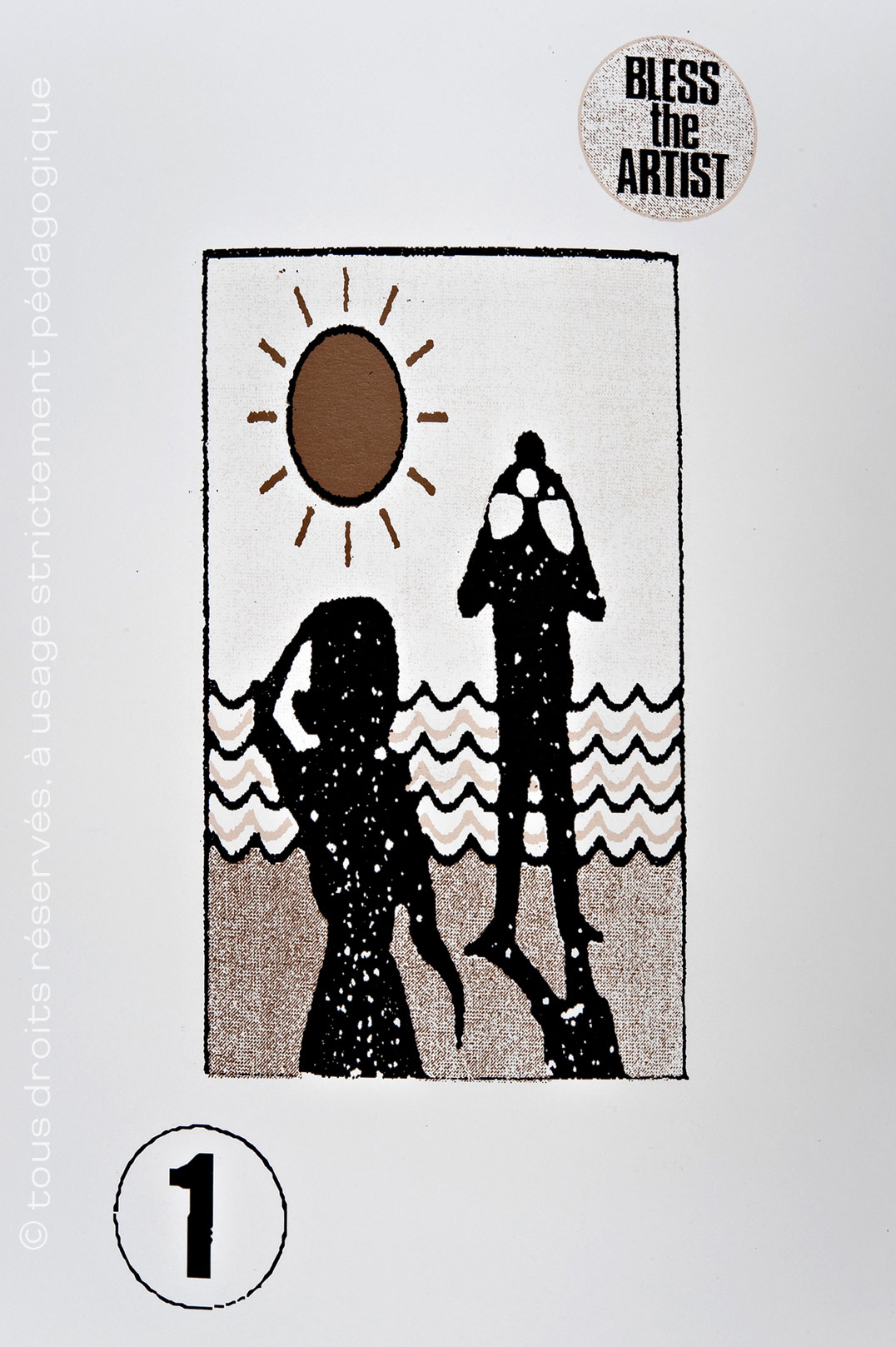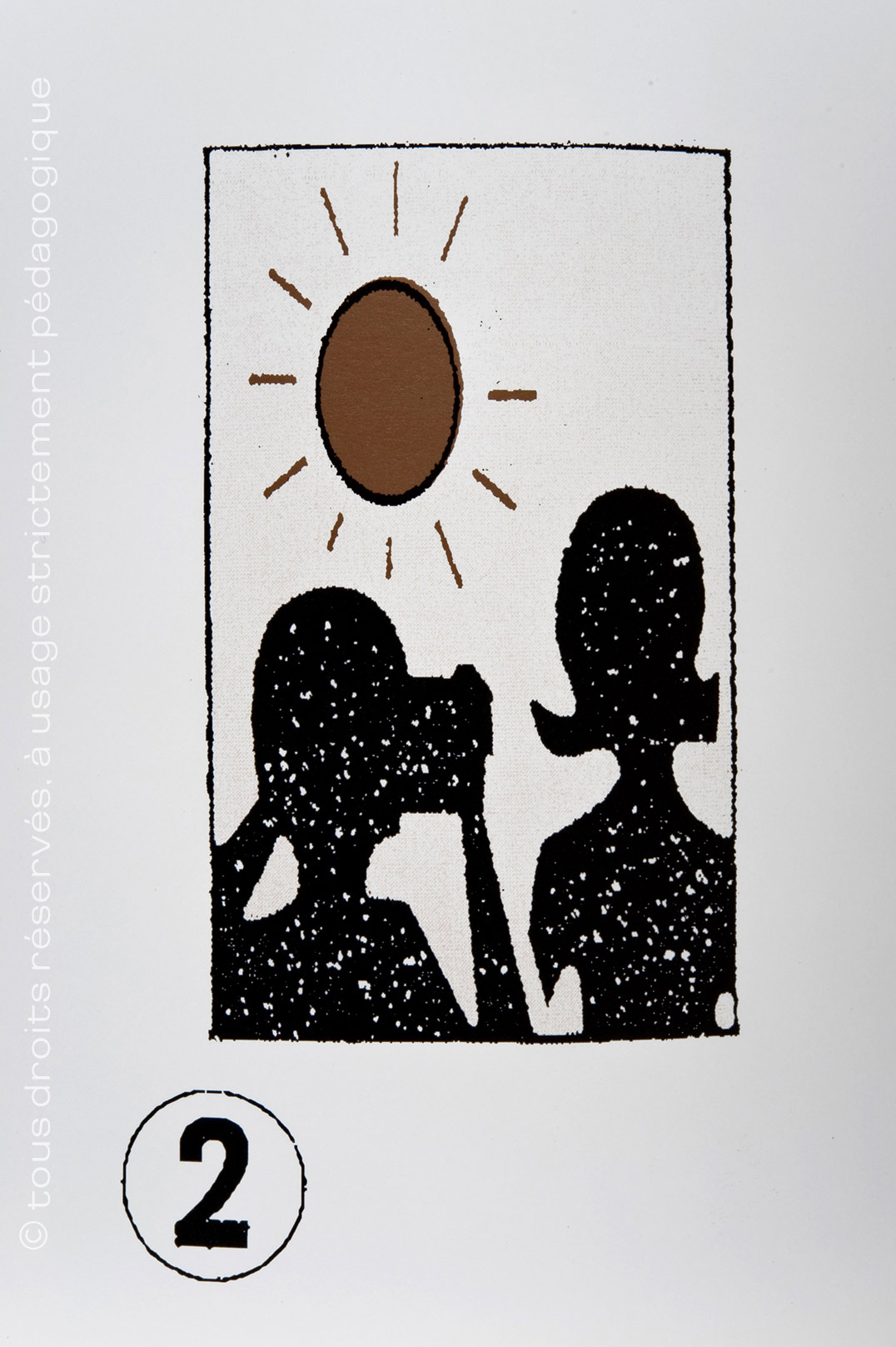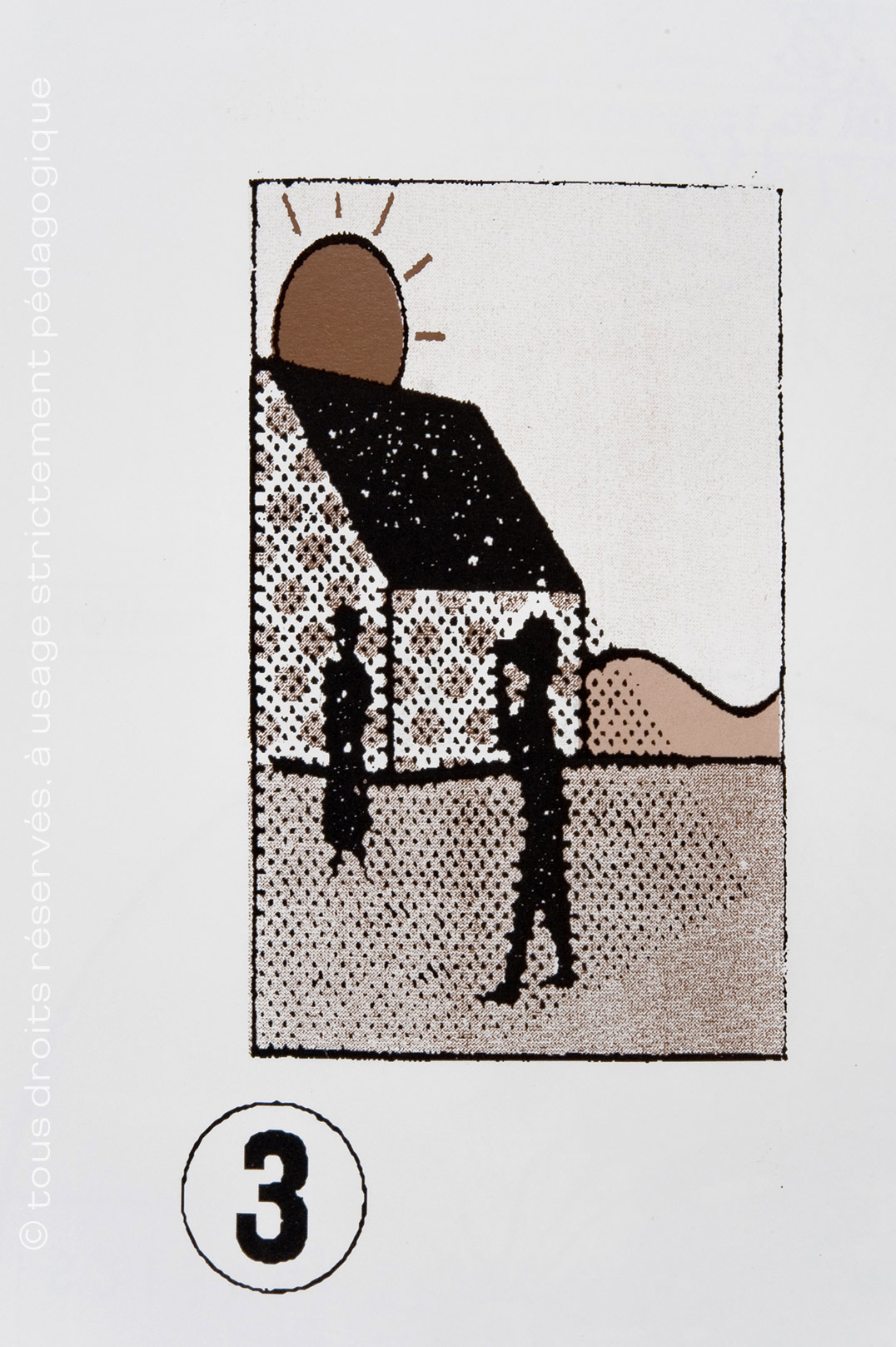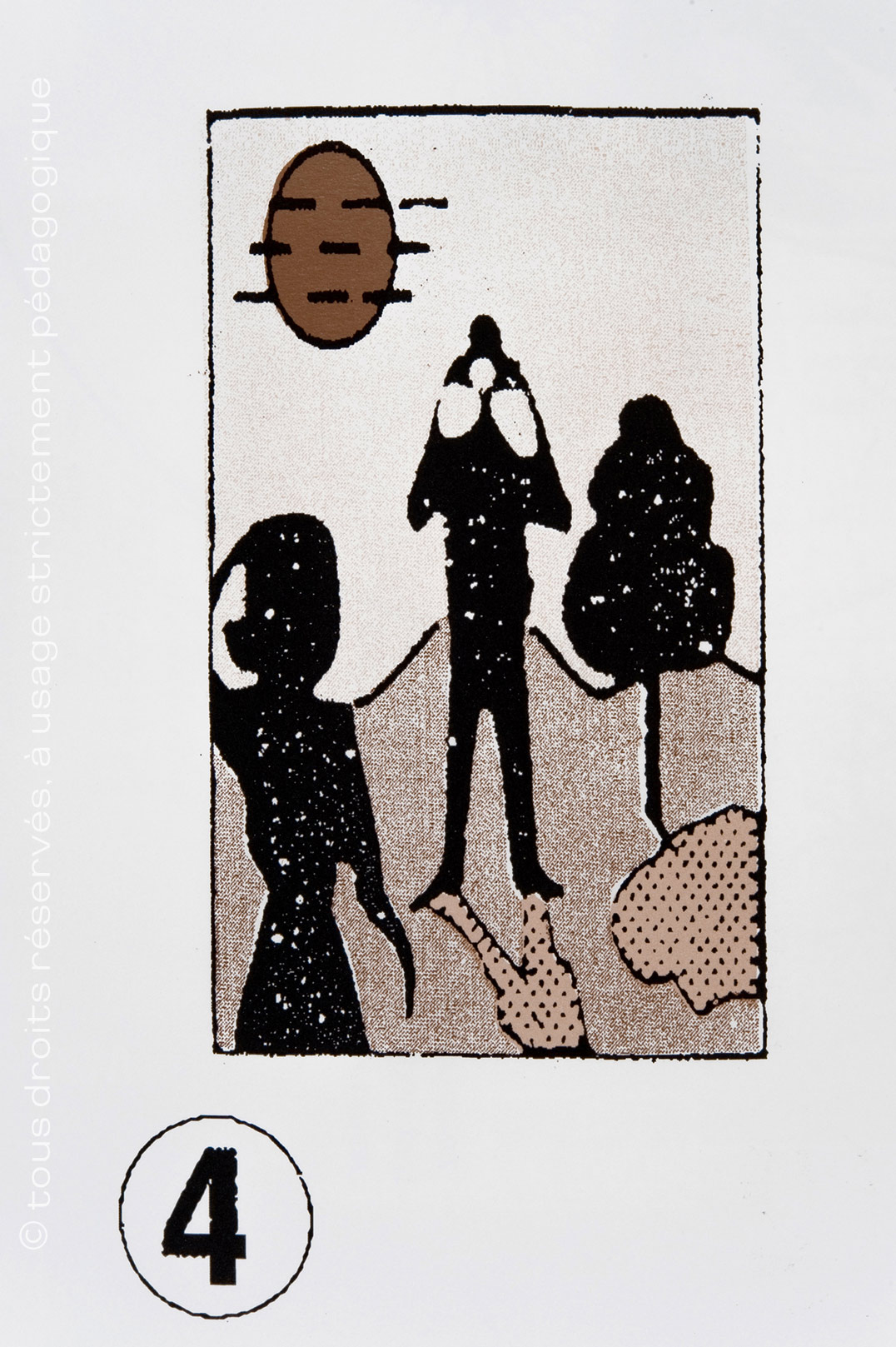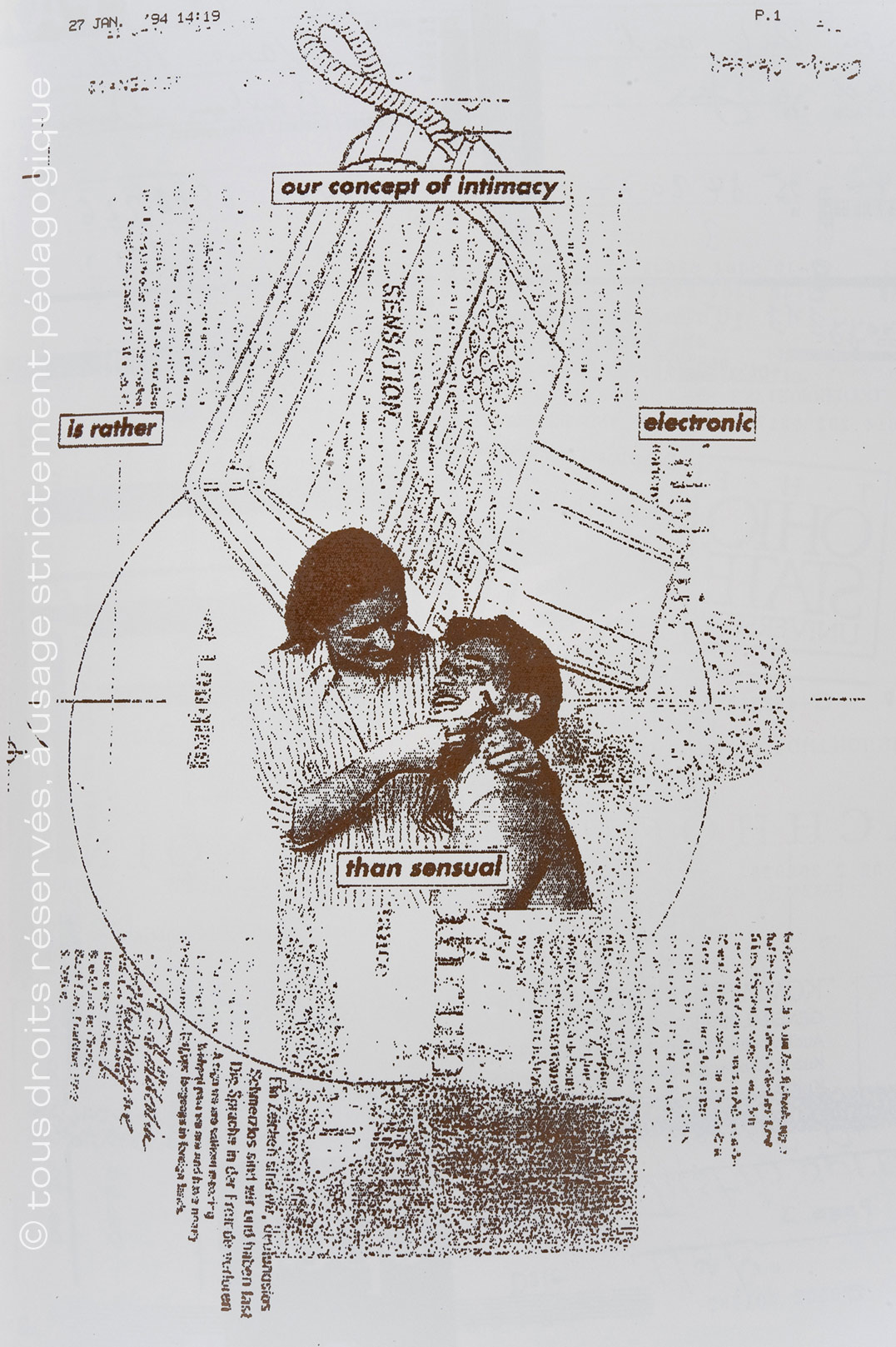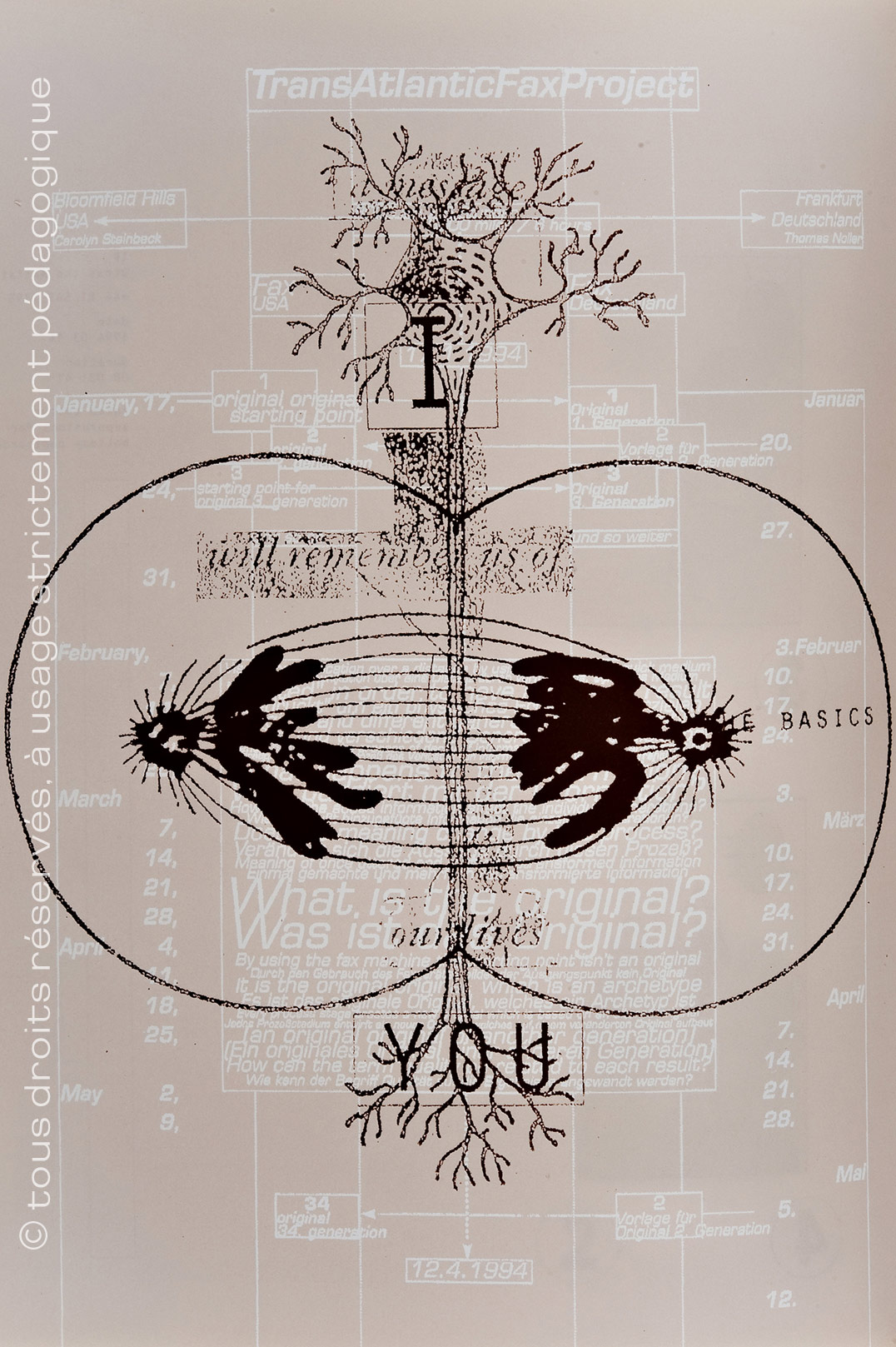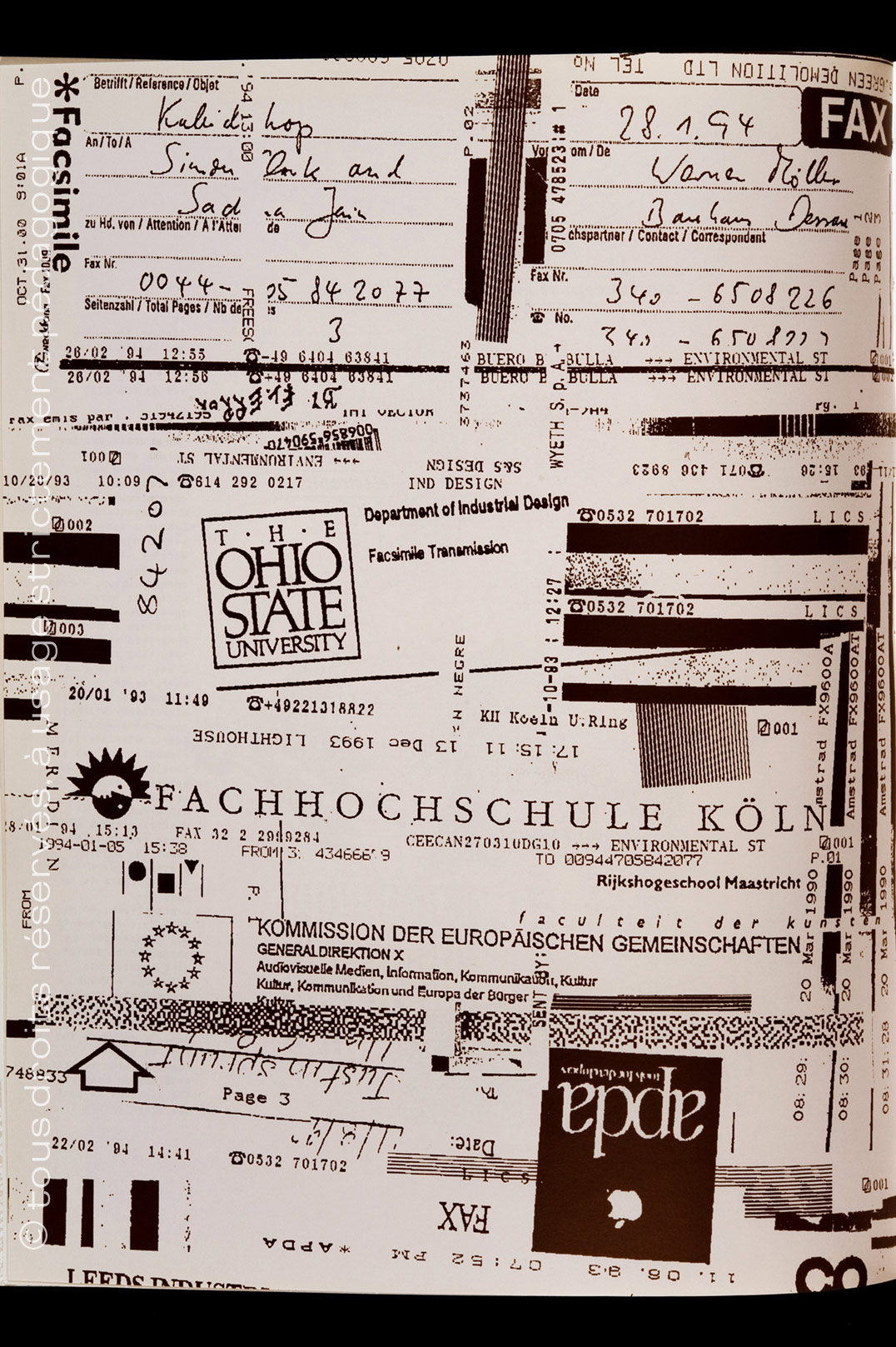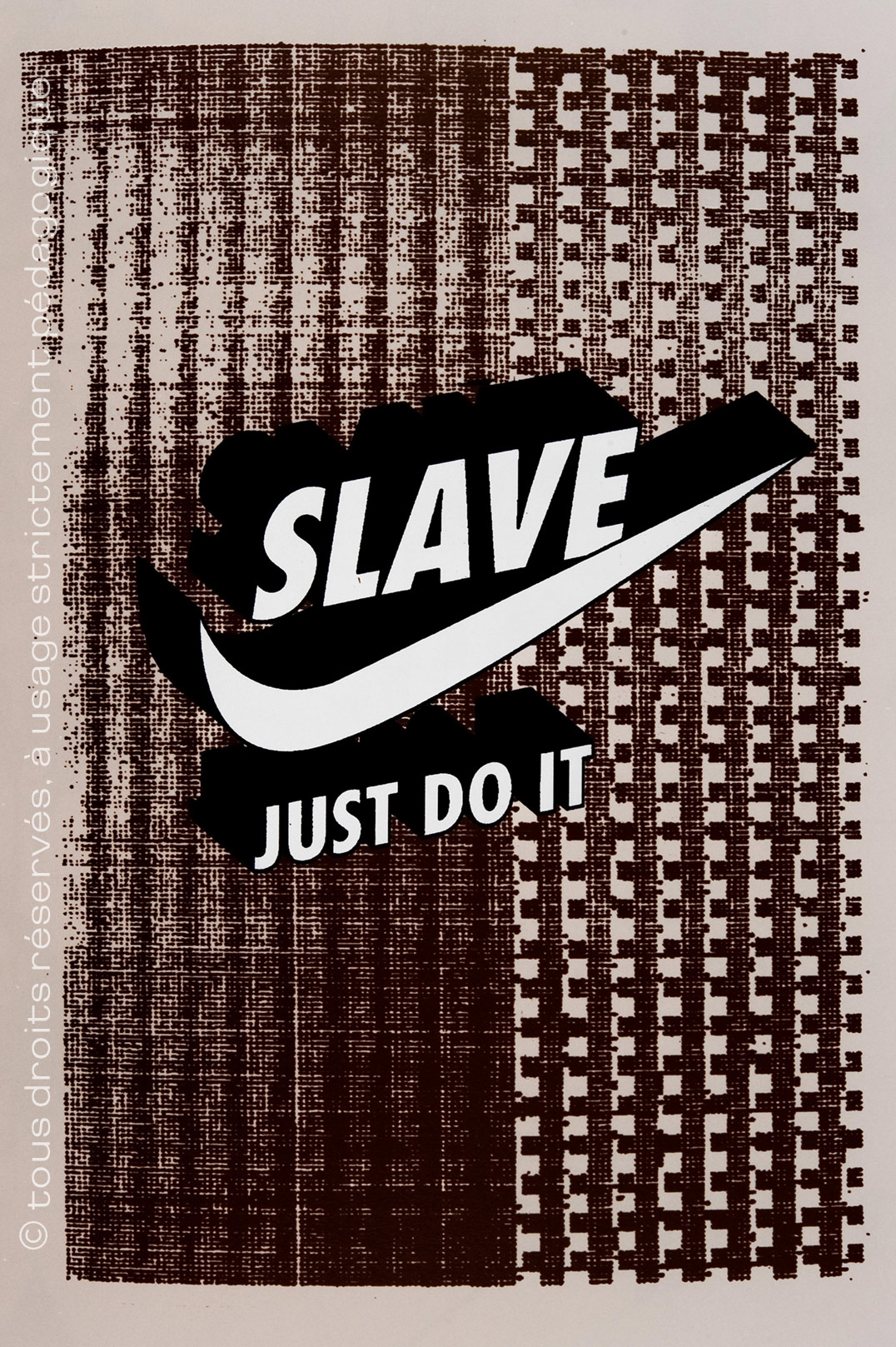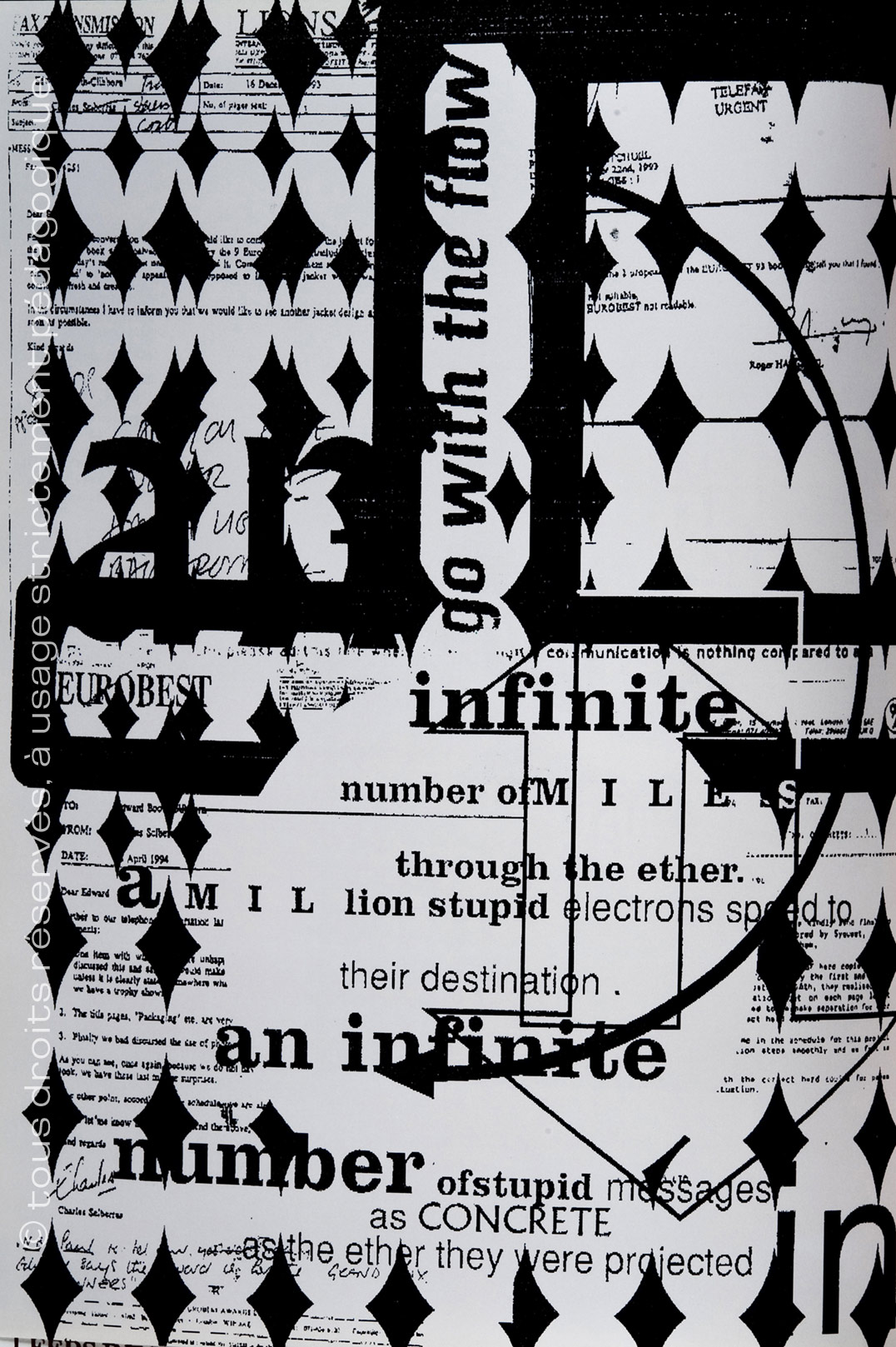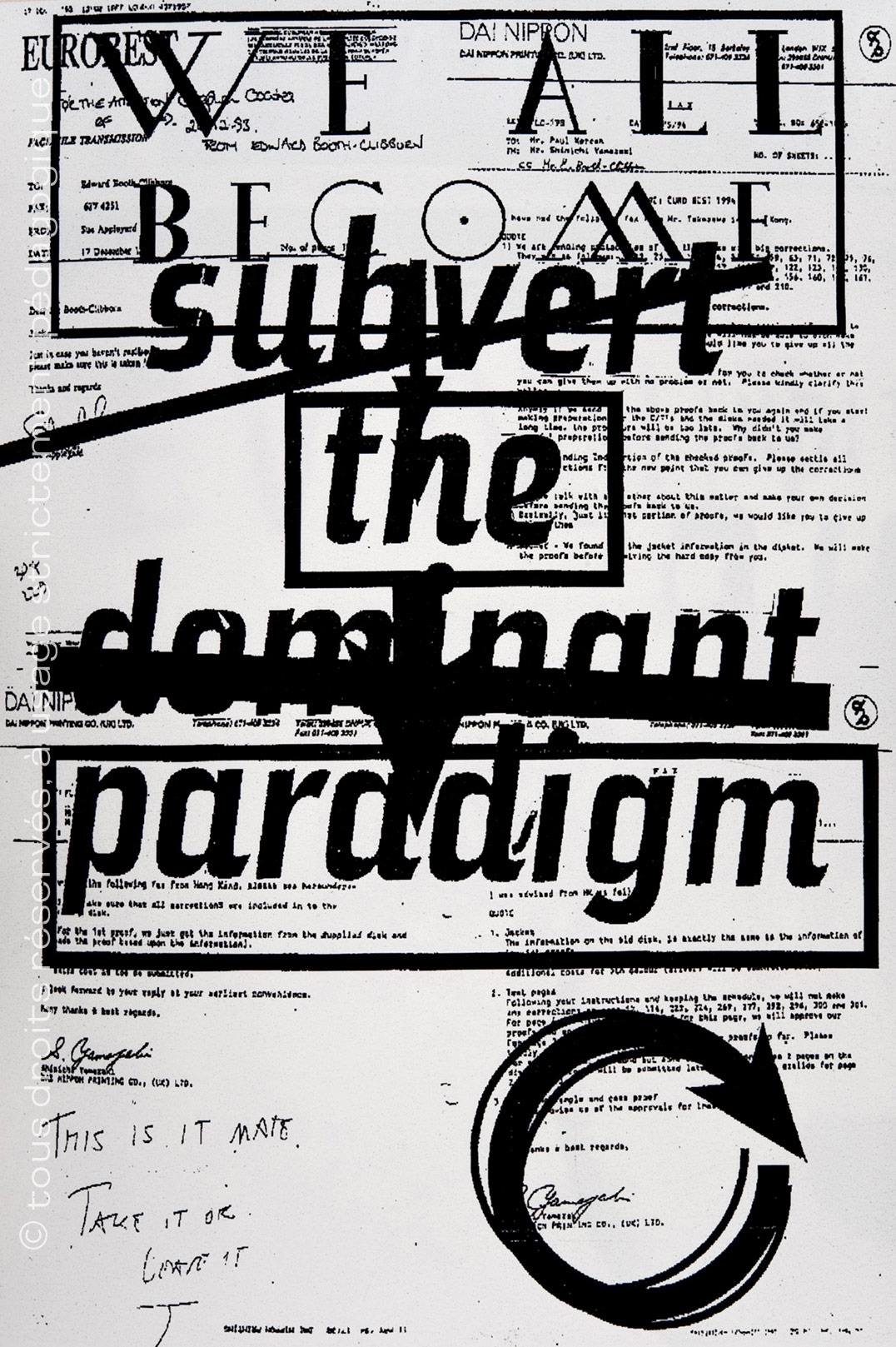
The Graphic Language of the Fax | de Edward Booth-Clibborn et Liz Farrelly (2/3)
Le livre d’Edward Booth-Clibborn et Liz Farrelly (suite): vous pourrez j’en suis sûr, le trouver encore «d’occasion» sur Amazon ou sur des sites spécialisées. Son intérêt est majeur. Il nous montre comment des artistes graphiques ont récupéré (comme souvent) une technologie pour la détourner et se l’approprier (aaaartistiquement parlant).
Ce que je retiens particulièrement de tout ce travail, est forcément de la fascination pour une renaissance du DaDa au travers des technologies pré-numériques. Ou comment un système de communication hyper normée, destiné à faire passer des messages fonctionnels (commandes, offres de service, confirmation de livraison, courrier entre clients et fournisseurs) a été détourné et perverti par la créativité des graphistes.
Le Fax a joué le même rôle que l’email durant près de 22 ans (de 74 à 96). Ce fut la première révolution postale qui déstabilisa les échanges de courrier traditionnels. Au point que très vite les bureaux de Poste ont du ajouter en catastrophe des machines Fax dans leur agence.
Et pendant que les artistes détournaient en «trashant» leurs courriers, des millions de Fax rendaient caduques le travail des coursiers et autres facteurs… Jusqu’aux lettres recommandées, qui prirent une «claque» le jour où les cours de justice acceptèrent la recevabilité juridique d’une trace faxée d’un message. Bien entendu, les télex qui jouaient encore un rôle prépondérant dans les échanges entre salles de marchés et les banques ne manquèrent pas de se doter de Fax normées et agrées par les autorités des marchés boursiers.
L’avènement du numérique était en marche. Les machines Fax, de plus en plus abordables se démocratisèrent pour accompagner les systèmes téléphoniques de Monsieur ToutleMonde…  vingt deux années d’une technologie annonciateur de la plus grande révolution des échanges dématérialisées par les emails.
Belle aventure dont les œuvres ci-dessous ne sont qu’un témoignage graphique des plus innovant. Et montrent par la même occasion que l’Artiste a toujours été au rendez-vous des innovations techniques tout au long de l’aventure humaine. FaxYou est une sorte de mémoire «façon Grottes de Lascaux» d’une immense révolution technique qui allait balayer tous les échanges sur la planète.
Les vitesses de transmission qui commencèrent à 6 minutes pour un A4 en 1974 atteignirent très vite avec la génération des G3 des allures de FGV (Fax Grande Vitesse), avec des temps de transmission de l’ordre de quelques secondes. En ce sens on peut même affirmer que le Fax a participé à la naissance d’une économie mondialisée.
The power of graphism, le poids des mots le choc du dessins ou des photos.
Comment ne pas réagir lorsque les formes se mélangent aux couleurs pour donner naissance à un message unique et donc puissant.